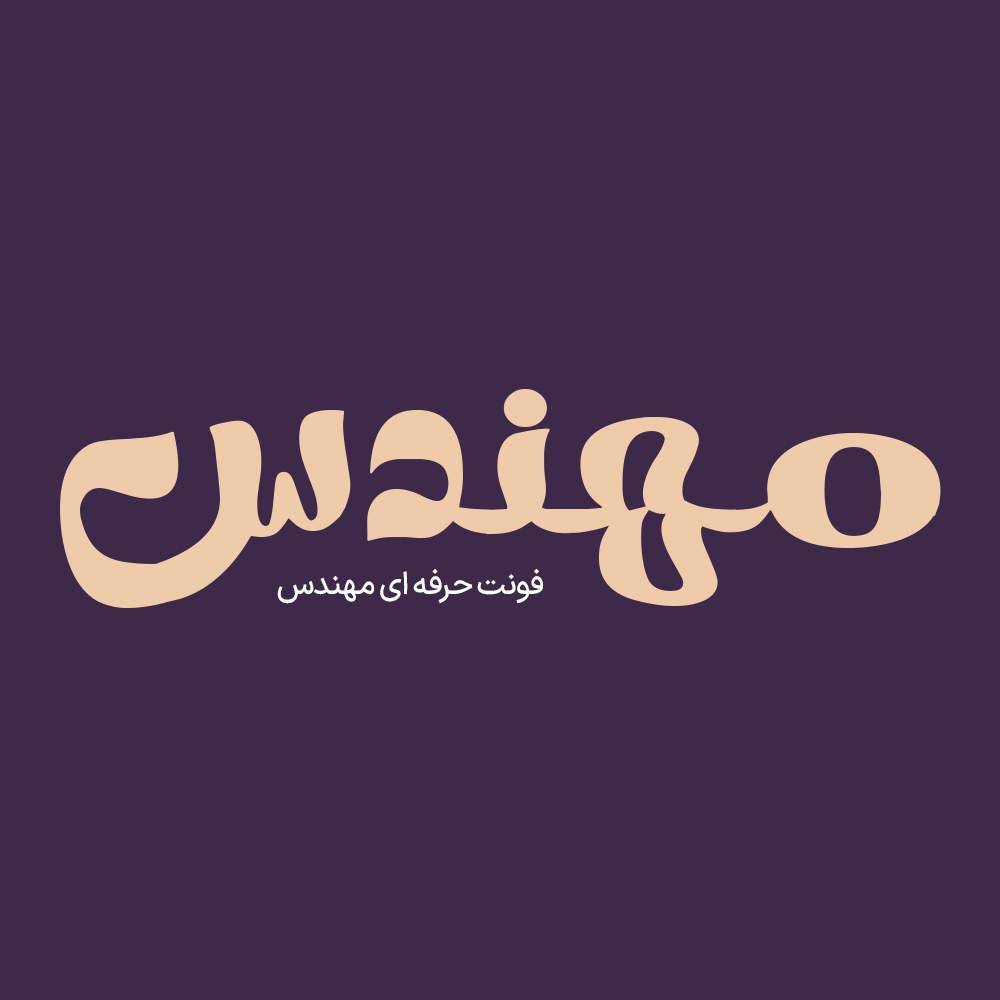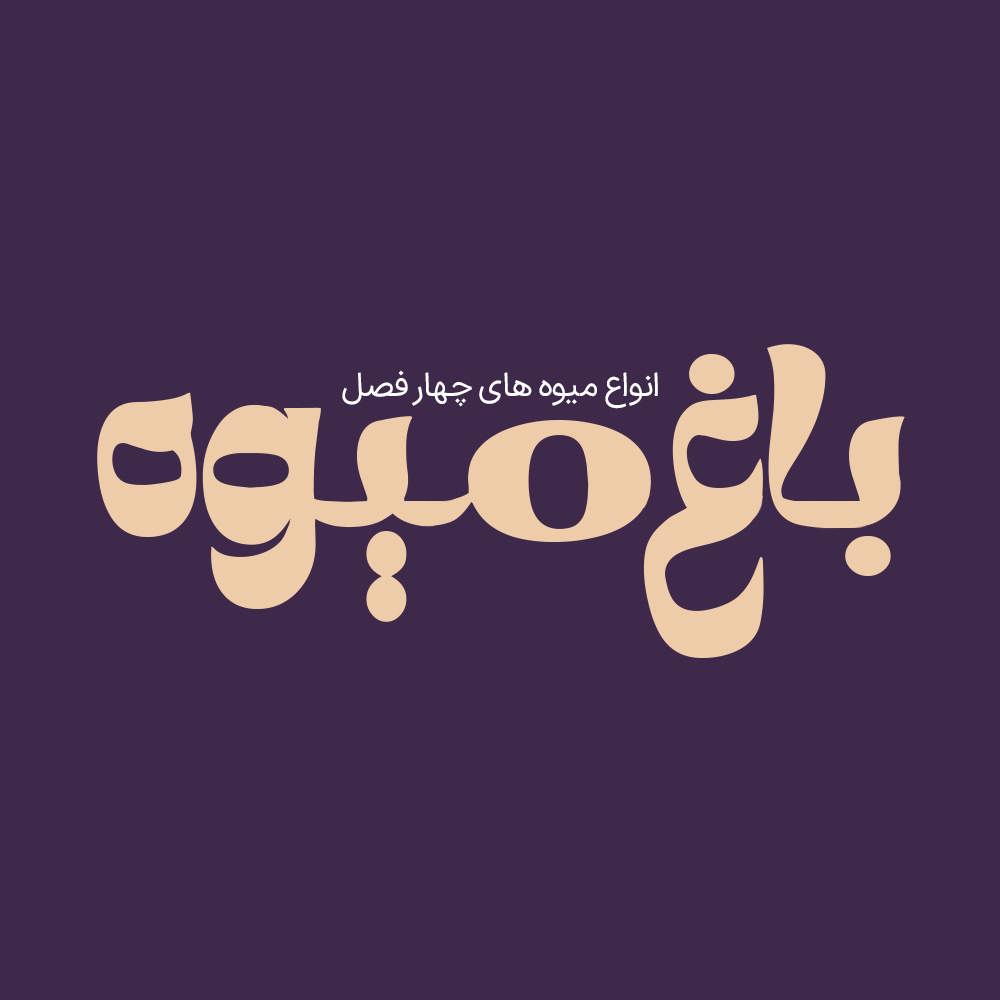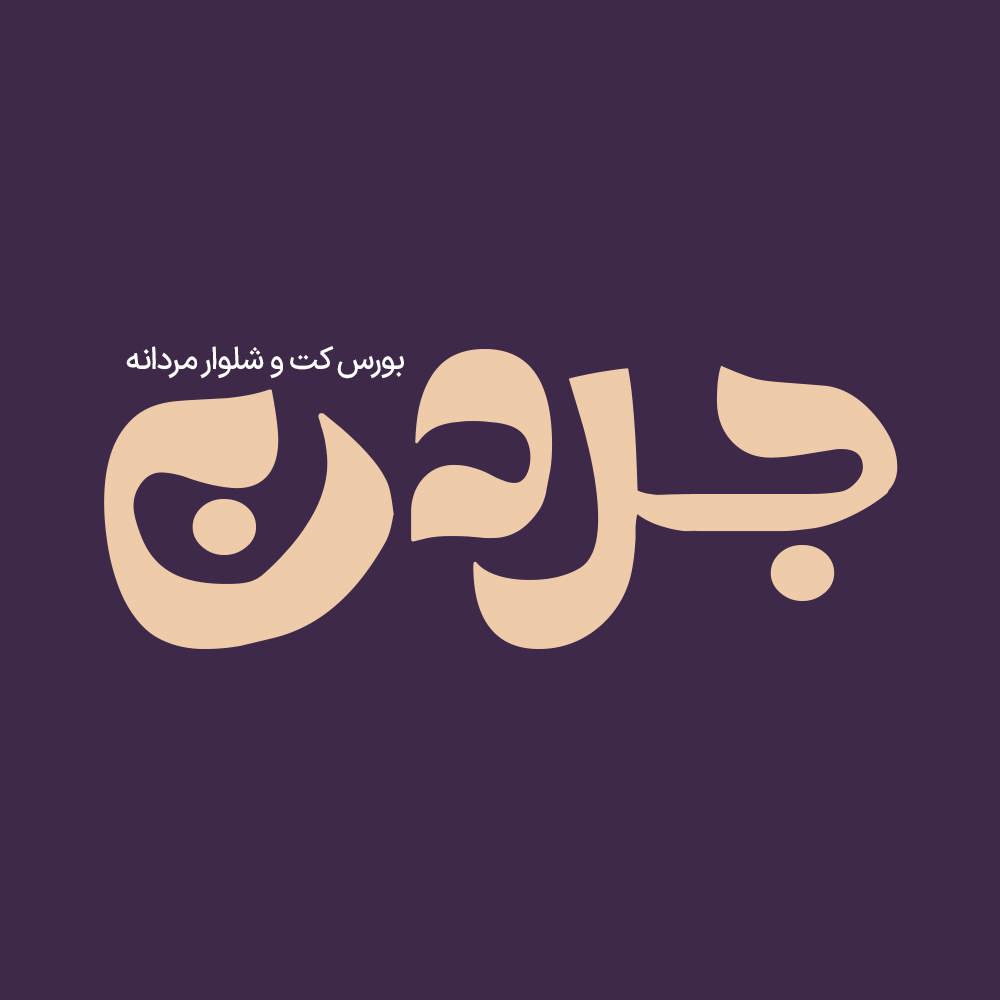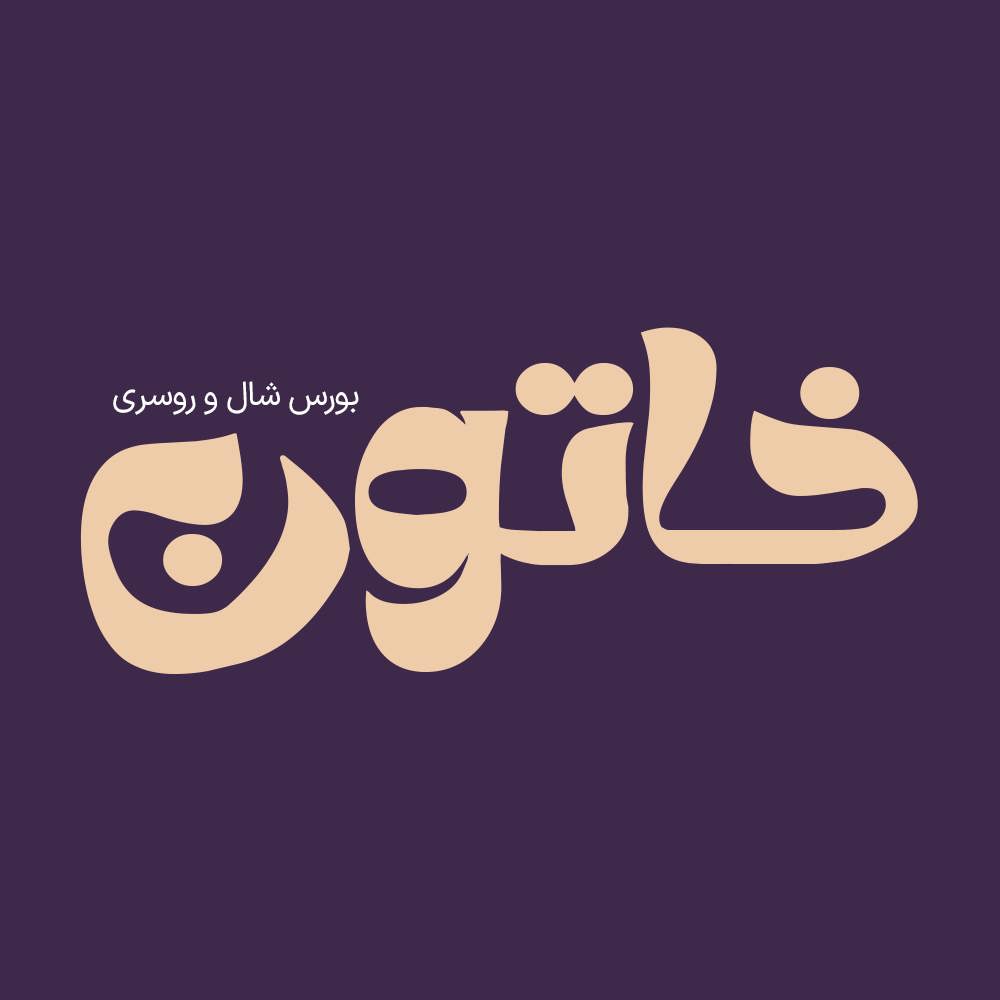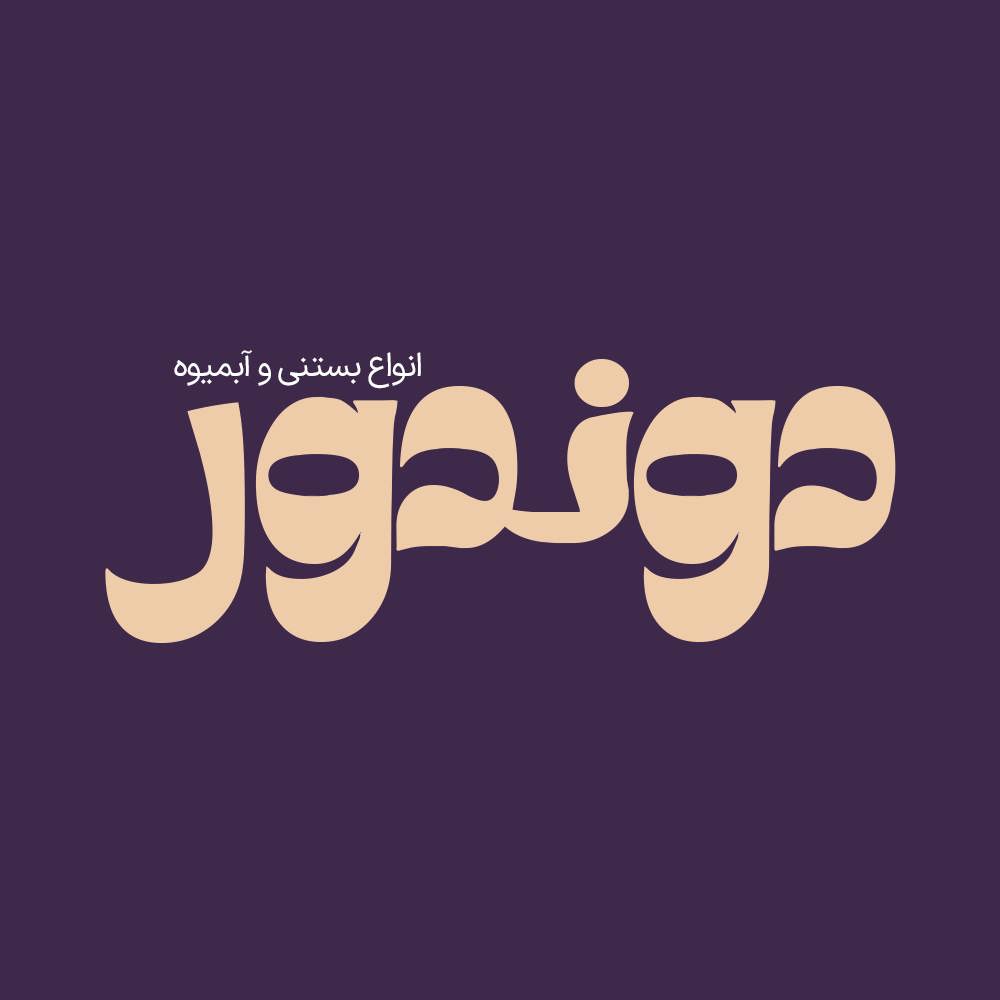
فونت فارسی مهندس Mohandes Font
فونت فارسی مهندس یک فونت نمایشی است که شخصیتی جسور، خلاق و مستحکم دارد. فونت فارسی مهندس برای عناوین و سطرهای کوتاه طراحی شده و با…
فونت فارسی مهندس یک فونت نمایشی است که شخصیتی جسور، خلاق و مستحکم دارد. فونت فارسی مهندس برای عناوین و سطرهای کوتاه طراحی شده و با وجود جدیت و استحکامش، دلنشین است. فونت مهندس انتخابی ایدهآل برای تیترها، عناوین، متنهای کوتاه، فضای تبلیغاتی و شبکههای اجتماعی است. این فونت با ساختار حروف خود مناسب استفاده در لوگوهای نوشتاری می باشد. همچنین از این فونت در طراحی تابلوهای چلنیوم هم به دلیل ساختار منحصر به فردش می توانید استفاده کنید. در ادامه برای شما نمونه تایپ های این محصول حرفه ای رو آماده کردیم که میتونید مشاهده کنید.
پیشنمایش و نمونه تایپ های فونت مهندس